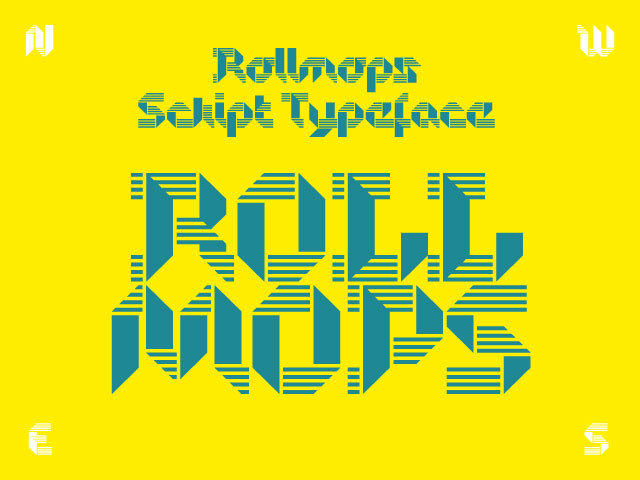
ROLLMOPS ist eine modular aufgebaute, experimentelle Schreibschrift, die mit der Idee spielt, aus einem endlosen Papierstreifen eine Textzeile zu falten. Der Gesamteindruck der Schrift ist technisch und modern, das Schriftbild sehr ungewöhnlich und charakteristisch! Verwenden lässt sich ROLLMOPS ausgezeichnet für rasterbasierte, geometrische Designs mit großen Lettern oder für Logotypes.
Spannend fand ich den Gedanken, eine Schreibschrift zu entwickeln, die nicht auf geschriebenen Vorlagen basiert. Dennoch finden sich viele Parallelen zum geschriebenen Buchstaben: Das Bedürfnis des Schreibers das Wort aus einem durchgehenden Strich zu entwickeln bleibt auch beim Falten erhalten. Und auch die Entwicklung der Buchstabenform aus der Federhaltung lässt sich auf den Knick-Winkel des Papierstreifens übertragen. Viele Probleme waren ähnlich zu gängigen Schriftentwicklungen aber an einigen Stellen mussten neue ungewöhnliche Lösungen gefunden werden, die ROLLMOPS ihren eigenständigen Charakter verleihen.
Rollmops Freefont
Felix Braden